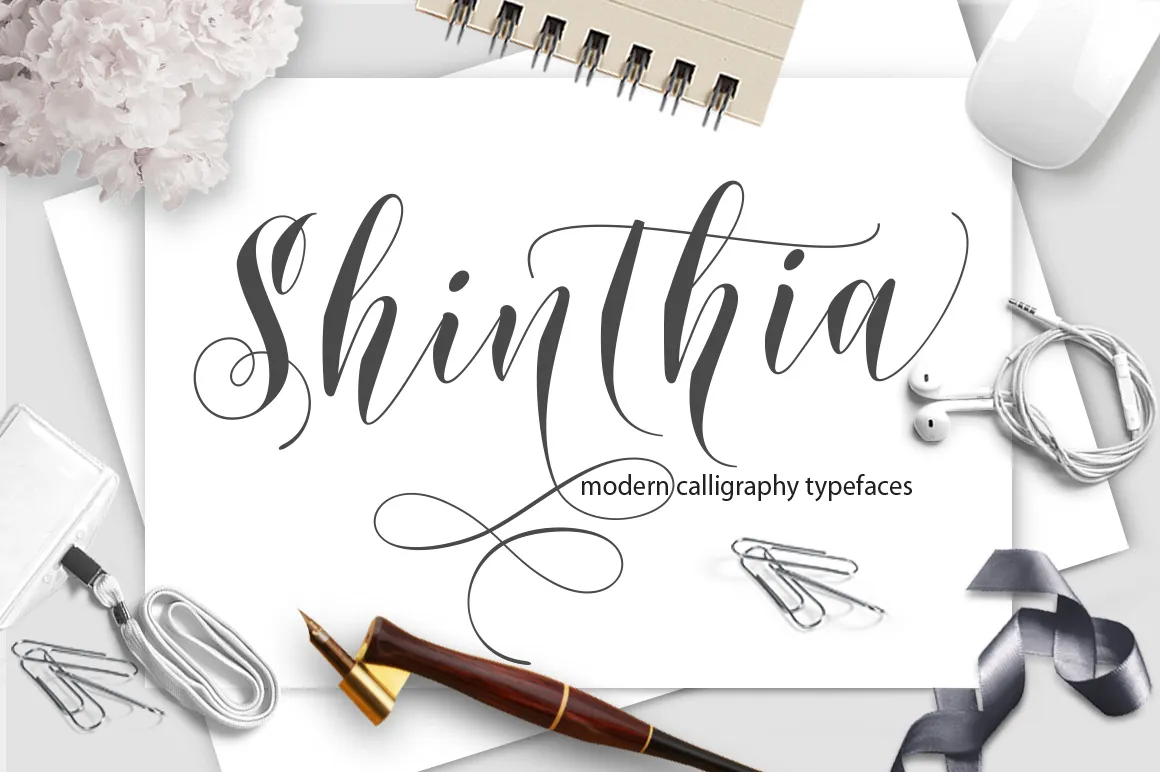
Shinthia Script Font
A Shinthia Script Font é uma fonte elegante que traz a autenticidade do estilo Blackletter em versões modernas e contemporâneas. Ela foi criada por Hamilton, o designer responsável pela criação desta fonte única e fascinante. Com suas ondulações fluidas e seu toque moderno, ela é perfeita para quem busca uma mistura arrebatadora entre clássico e atual. A Shinthia Script oferece uma versatilidade impressionante que a torna ideal para uso em diversos formatos de design. Possui um formato suave e fluido, adequado tanto para letras grandes como pequenas, sejam esses títulos, assinaturas, logotipos ou até cartas devidamente personalizadas. Seja para enviar convites de casamento, criar uma identidade visual forte, fabricar etiquetas de produtos ou mesmo para adicionar um toque único em cartazes e embalagens. Esta fonte é perfeita para qualquer designer que valoriza a estética única enquanto busca um elemento moderno na paleta de recursos gráficos. Em suma, Shinthia Script é uma escolha ideal tanto para quem procura um design clássico quanto para aqueles buscando algo contemporâneo e inovador em sua próxima criação visual.